Guardando un logo o un’immagine pubblicitaria vi siete mai chiesti “ma che font è?” Sicuramente sì! A me è capitato parecchie volte di guardare una scritta e di voler sapere con quale carattere tipografico è stata realizzata. Se pensate che per identificare il font utilizzato in un’immagine vi serva un mago o l’occhio raffinato di un grafico esperto vi sbagliate! In questo articolo vi mostrerò come identificare in pochi istanti e con assoluta precisione il font utilizzato in un logo o in un’immagine digitale.
La magia del font perfetto
Sicuramente vi è capitato di guardare una scritta e dire “wow! ma quel font è bellissimo”. Non è necessario essere dei grafici per apprezzare il carattere tipografico di una scritta. Il font, infatti, è un elemento distintivo di un’immagine e come tale è in grado di attirare l’attenzione di chi guarda: le sue curve, le sue forme, il suo spessore, ecc. sono aspetti caratterizzanti della scritta e sono in grado, se utilizzati correttamente, di rafforzare il messaggio che si vuole veicolare, rendendolo più penetrante e distintivo. La scelta del font per una scritta, quindi, non è una cosa di poco conto e quando si trova, magari per caso, il “font perfetto” per i propri fini di certo non bisogna lasciarselo scappare.
Quando può essere utile identificare il font di un’immagine?
Le situazioni nelle quali può tornare utile trovare il font utilizzato all’interno di un’immagine sono innumerevoli. A volte si tratta di semplice curiosità, altre volte è una vera e propria necessità lavorativa. Facciamo qualche esempio:
- ti è stato chiesto di rifare il logo di un’attività, apportando alcune variazioni al’immagine originale, ma il cliente non si ricorda il font utilizzato per realizzarlo;
- ti è stato commissionato un lavoro grafico ed il cliente ti chiede di utilizzare lo stesso carattere utilizzato nella comunicazione di un competitor;
- devi realizzare un’immagine per celebrare un evento collegato ad un brand famoso (ad esempio un film o una serie TV) e ti viene chiesto di utilizzare lo stesso font per creare immagini pubblicitarie ad hoc.
Effettuare il riconoscimento del font in un’immagine mediante OCR
In tutte queste (e molte altre situazioni) può rivelarsi molto utile avere un modo per identificare, in modo semplice e veloce, il font utilizzato nell’imagine di riferimento. Per fortuna esistono diversi servizi on-line che consentono di identificare automaticamente il font di una scritta presente in una foto o in un’immagine digitale! Questi sistemi sono detti, in inglese, font detector, font finder o font recognizer.
Il loro funzionamento è piuttosto semplice: si effettua l’upload dell’immagine contenente la scritta che si vuole analizzare e si attende che lo strumento prescelto svolga il lavoro restituendoci il nome del font! Il funzionamento di questi siti web si basa sulla tecnologia OCR (optical character recognition) per il riconoscimento ottico dei caratteri che offre un livello di precisione molto buono: se si tratta di un font “censito” dal tool di riconoscimento utilizzato la risposta è assicurata. Ovviamente maggiore è la qualità dell’immagine più alta sarà la possibilità di identificare correttamente i font in essa utilizzati.
Di seguito vi presento un elenco dei migliori siti web che offrono un servizio di riconoscimento dei caratteri tipografici utilizzati nelle immagini.
WhatTheFont
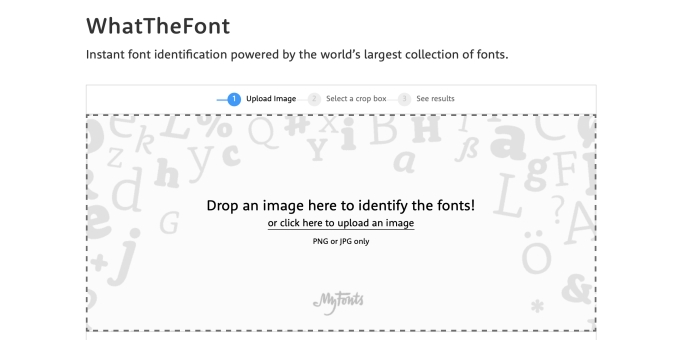
WhatTheFont è uno strumento automatico di riconoscimento dei font utilizzati in un’immagine fornito dal sito web MyFonts, uno dei più grandi database online di font con più di 130.000 caratteri tipografici censiti. Questo tool utilizza il deep learning per cercare nel database dei font e trovare la migliore corrispondenza per i caratteri presenti nella foto o immagine caricata. Funziona bene anche quando c’è più di un carattere in un’immagine: basta caricare l’immagine e fare clic sul carattere che si desidera identificare!
What Font Is?
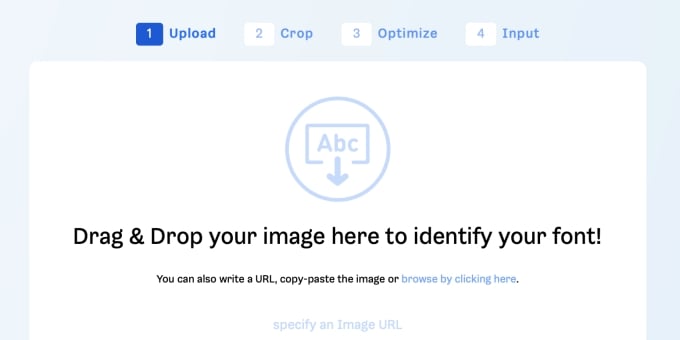
What Font Is? Che font è? Questa è la domanda cui si prefigge di rispondere questo utilissimo sito web. Basta effettuare l’upload dell’immagine interessata per effettuare automaticamente il riconoscimento dei font utilizzati nelle scritte al suo interno. Per i migliori risultati è opportuno caricare un’immagine di buona qualità in cui il testo non risulti distorto o disturbato. Il sistema utilizza l’intelligenza artificiale per trovare il carattere utilizzato e promette di offrire una risposta in circa il 90% dei casi.
Font Identifier (by Font Squirrel)
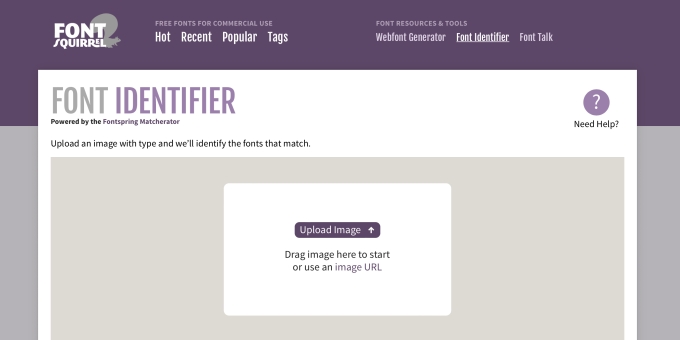
Questo servizio, fornito da sito Font Squirrel, promette di identificare con precisione i caratteritipografici utilizzati per realizzare le scritte presenti in un’immagine. E’ possibile effettuare l’upload dell’immagine che si vuole analizzare oppure, se questa è disponibile online, importarla semplicemente indicandone la URL.
Fontspring Matcherator
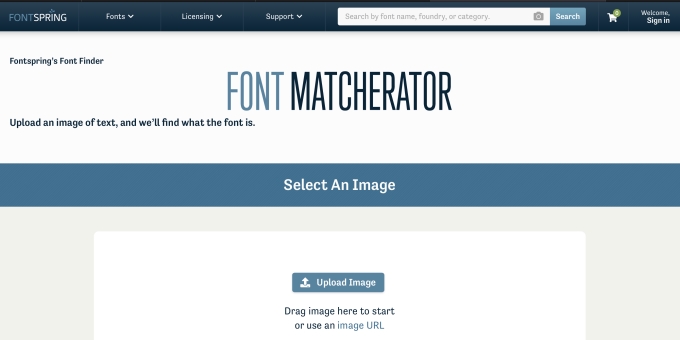
Questo sito web fornisce uno strumento di rilevazione automatico dei font utilizzati in un’immagine: è sufficiente caricare la foto o l’immagine attraverso il modulo di upload per effettuare il riconoscimento dei caratteritipografici presenti al suo interno. Questo strumento gratuito di ricerca dei font promette di cercare in un catalogo di oltre 900.000 font (gratuiti e a pagamento), tutti disponibili per il download o l’acquisto all’interno del sito stesso.
LikeFont
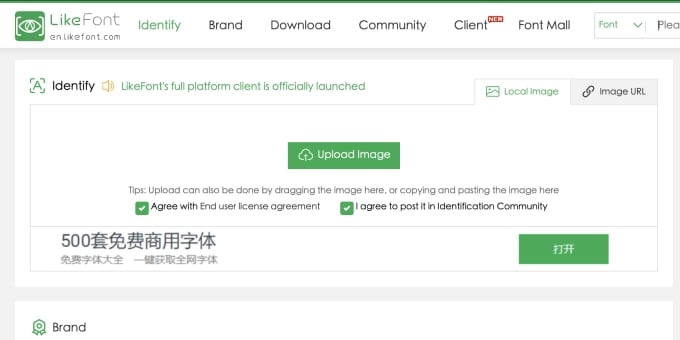
Il sito LikeFont consente di identificare i font utilizzati all’interno di un’immagine. Per avviare il processo di riconoscimento dei caratteri tipografici è necessario, ovviamente, effettuare l’upload dell’immagine digitale contenente le scritte che si desidera analizzare.